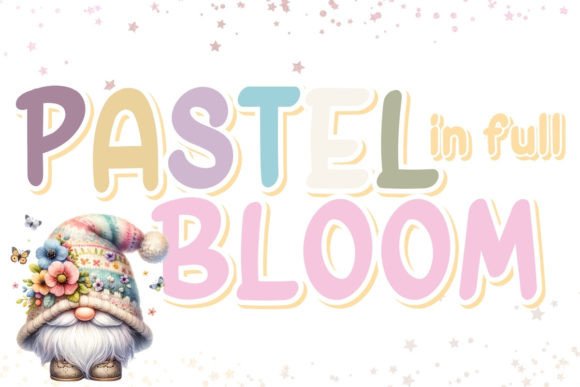
Pastel in Full Bloom
Pastel in Full Bloom와 같은 κ³ ν’ˆμ§ˆ μžμ‚°μ„ μ°Ύκ³  μžˆλ‹€λ©΄ 이 프리미엄 νŒ¨ν‚€μ§€λŠ” 창의적인 ν”„λ‘œμ νŠΈλ₯Ό μœ„ν•œ ν™˜μƒμ μΈ μ„ νƒμž…λ‹ˆλ‹€.
μ •λ°€ν•˜κ²Œ μ œμž‘λœ Pastel in Full BloomλŠ” κΉ”λ”ν•œ 벑터, λΆ€λ“œλŸ¬μš΄ νƒ€μ΄ν¬κ·Έλž˜ν”Ό 및 μ•ˆμ‹¬ν•  수 μžˆλŠ” μƒμ—…μš© λΌμ΄μ„ μŠ€λ₯Ό μ œκ³΅ν•©λ‹ˆλ‹€.
POD(μ£Όλ¬Έν˜• 인쇄) μ œν’ˆ, κ²°ν˜Όμ‹ μ΄ˆλŒ€μž₯ λ˜λŠ” μ†Œμ…œ λ―Έλ””μ–΄ κ·Έλž˜ν”½μ„ λ§Œλ“€ λ•Œ Pastel in Full BloomλŠ” 이상적인 μ„ νƒμž…λ‹ˆλ‹€.